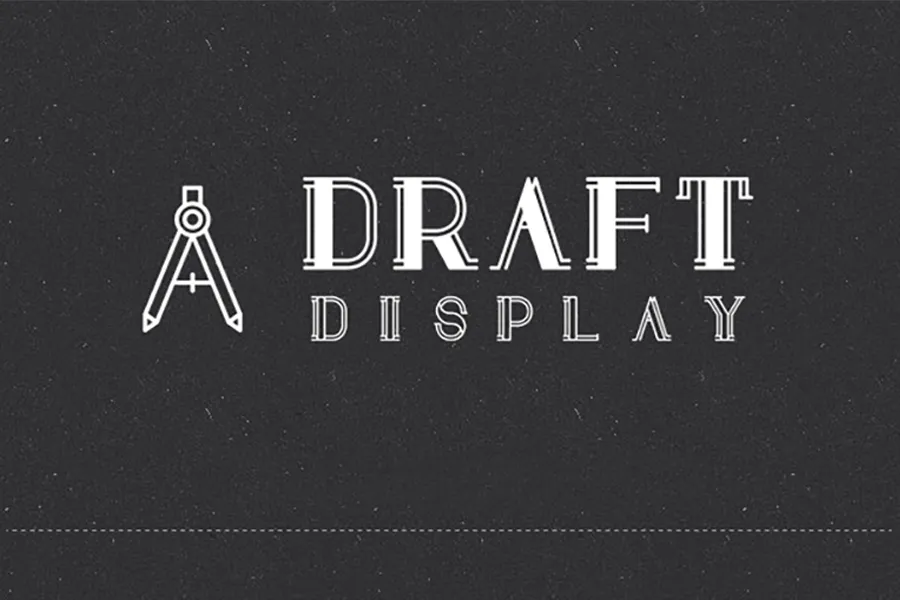
A fonte Draft Display é uma elegante escolha para qualquer projeto que busca um toque moderno e criativo no seu design. Desenvolvida pela designer Camille San Vicente, esta fonte está disponível gratuitamente e oferece ambos os tipos de letras (maiusculas e minusculas). Ideal tanto para gráficos digitais quanto para materiais impressos, Draft Display possui uma personalidade única que se destaca em qualquer projeto. Seja ela usada para criar headlines chamativas ou detalhes sutis em designs de logotipos, a fonte Draft Display certamente fará sua marca e irá complementar seu trabalho de forma excepcional. É um verdadeiro atalho ao design moderno e sofisticado que é tão valorizado no nosso mercado atual.